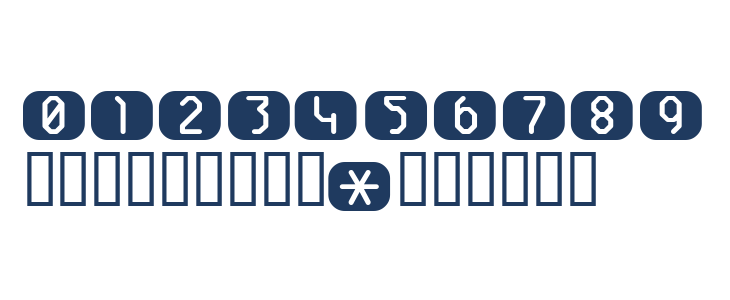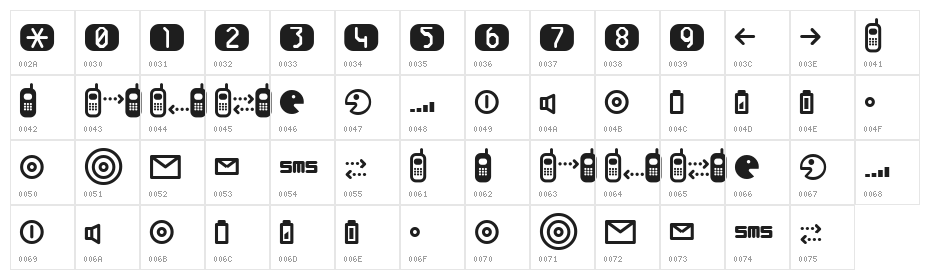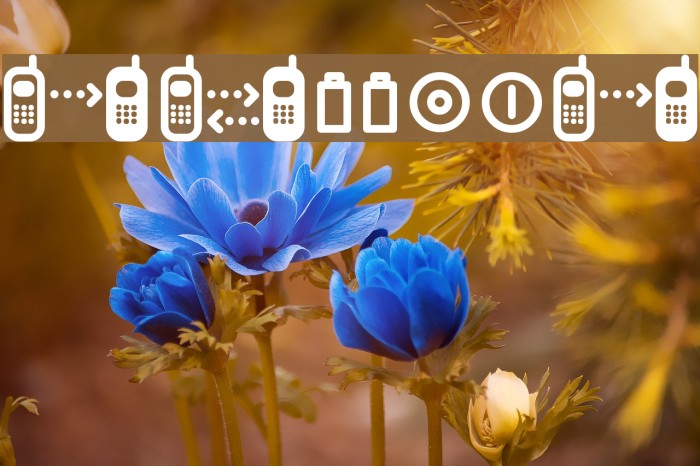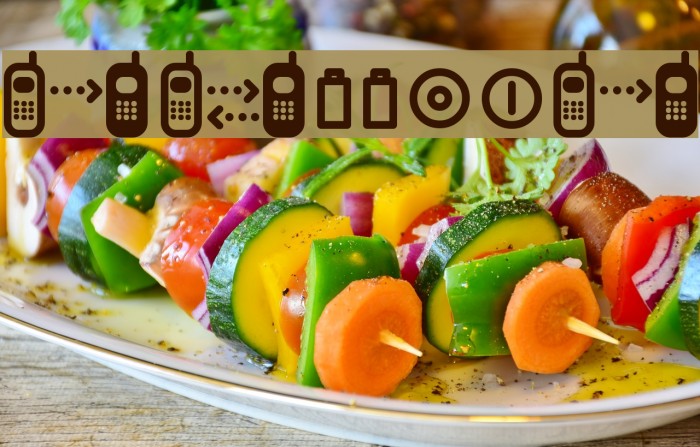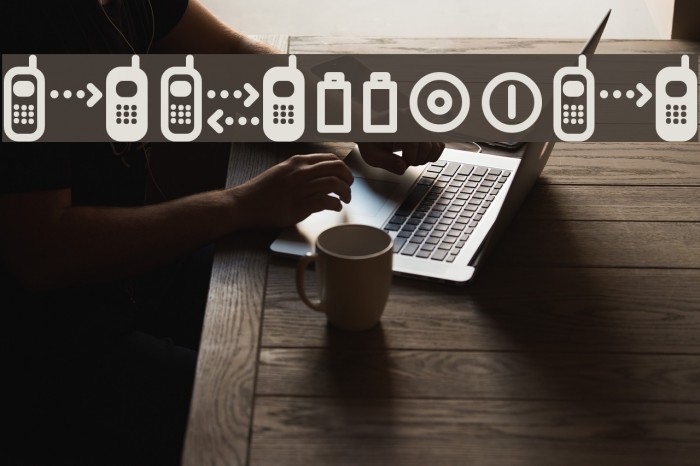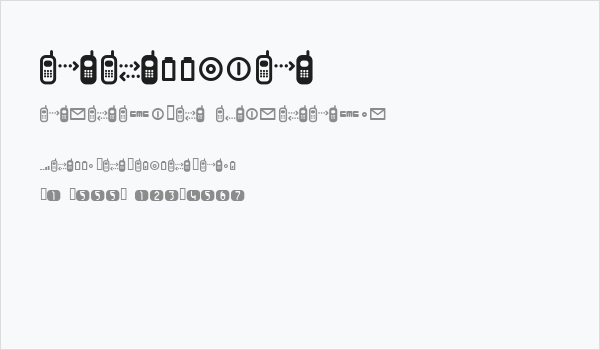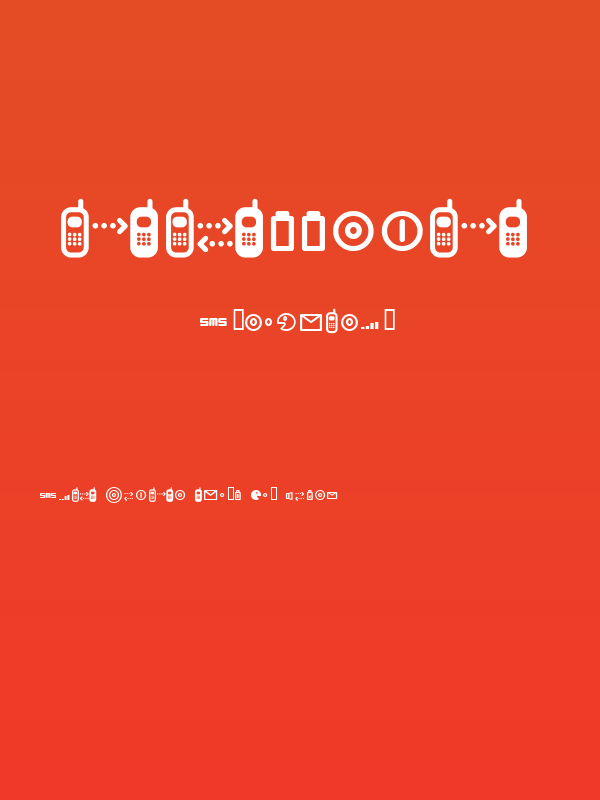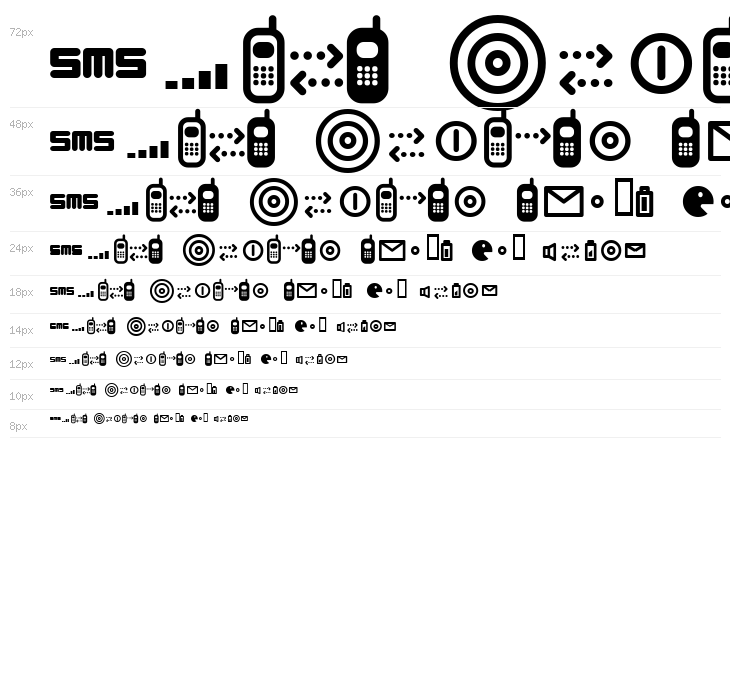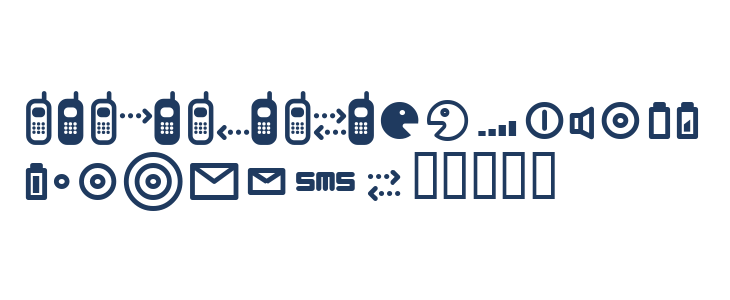
cellpic Font
| Caso d'uso | Logos, App interfaces, Digital media |
| Progetti proposti | Ideal for technology-related branding, app interfaces, digital communication materials, and educational tools about mobile technology. |